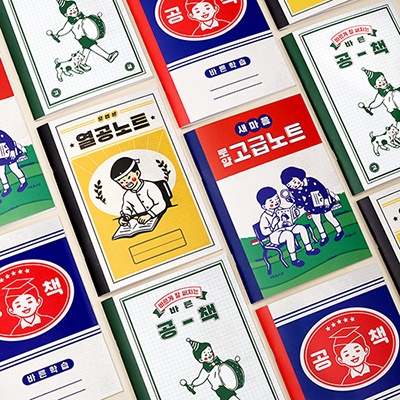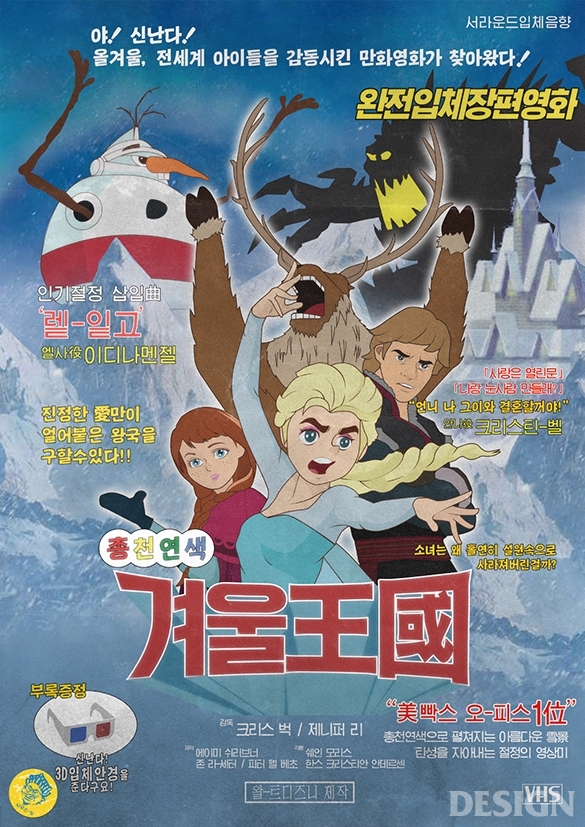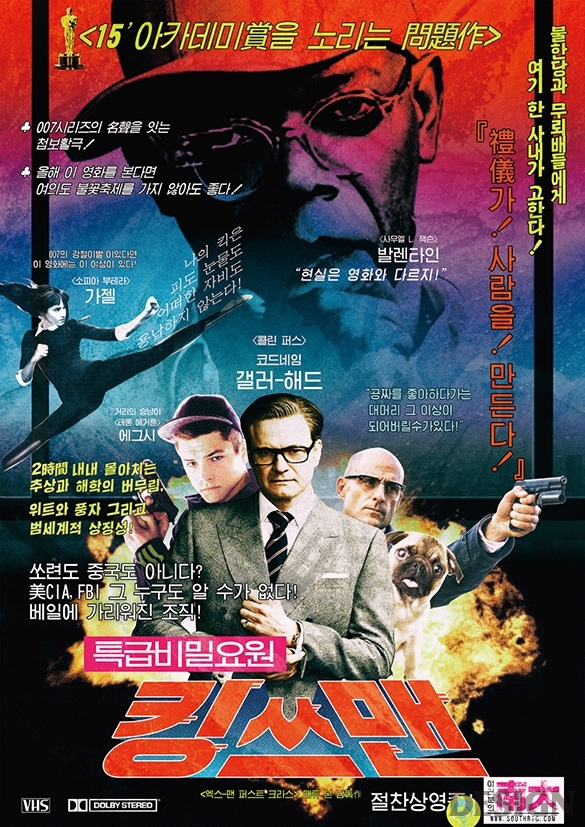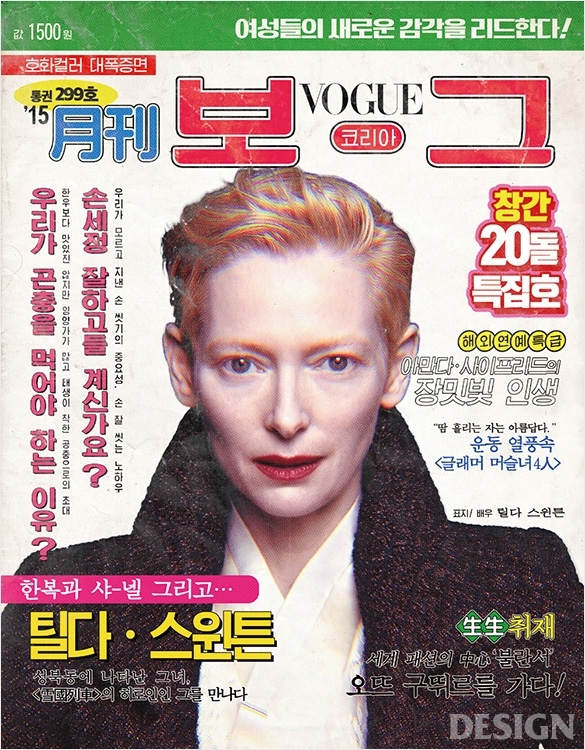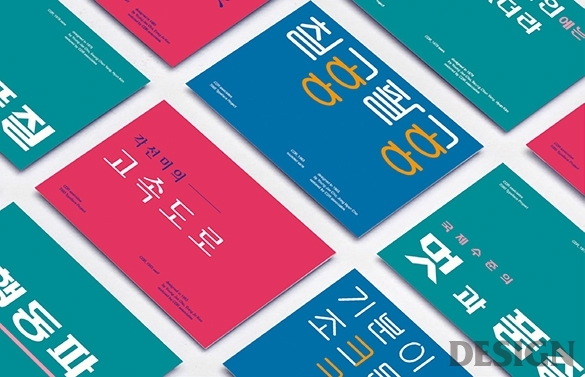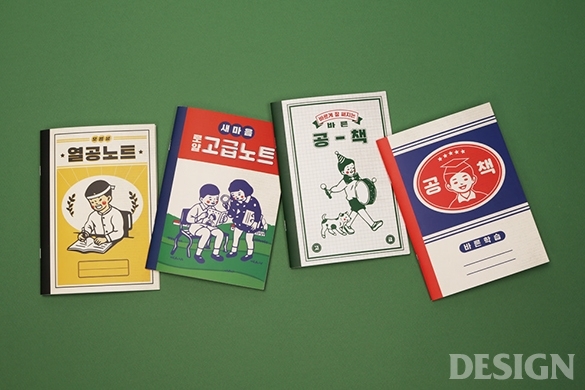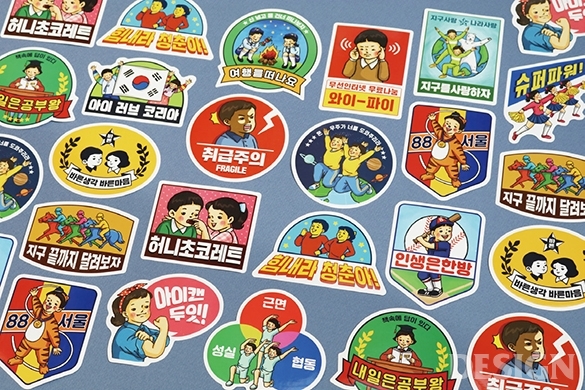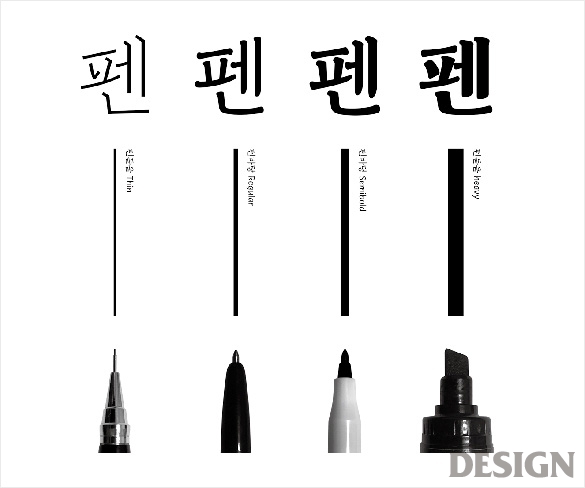
레트로 그래픽의 부상
2000년대 중반 들어 고개를 들기 시작한 레트로풍 타이포그래피와 그래픽 디자인은 이제 한국 디자인계에서 하나의 기조로 완전히 자리 잡은 모습이다. 이에 대한 심도 깊은 연구가 부족하다는 사실이 놀라울 정도다. 2000년대 말 붕가붕가레코드의 수석 디자이너 김기조가 선보인 레터링 작업(비록 이를 온전히 레트로로 보긴 어렵지만)은 당시 젊은 그래픽 디자이너들 사이에 적잖은 반향을 일으켰다. 수공업 소형 음반사를 지향하던 붕가붕가레코드는 크래프트지에 레터링을 입힌 라벨지를 부착하는 방식으로 비용을 절감했는데 그 모습이 영락없이 1970년대 말 폴라 셰어Paula Scher의 CBS 레코드의 아트 디렉터 시절을 연상시킨다. 제한된 예산에서 효과적인 결과물을 만들어야 했던 폴라 셰어의 상황이 2000년대 말 국내 인디 음반사의 그것과 일맥상통하는 것이다. 비슷한 시기에 젊은 타이포그래퍼들을 중심으로 그 옛날 도안사나 소위 간판장이의 글자를 모방한 것이 유행처럼 번져나가기도 했다.1) 이후 그래픽 디자인계에서 레트로 스타일은 여러 세대의 디자이너와 디자인 회사의 손길을 거치며 다양한 양상으로 표출됐다. 젊은 디자이너들은 레트로풍의 키치적 표현을 자신의 아이덴티티로 삼았고 기업들 역시 레트로를 앞세운 제품으로 시장을 공략했다. 디자인 저술가 전가경의 글은 그래픽 디자인, 특히 타이포그래피에서 다양하게 나타나는 레트로의 흐름을 짚어보는 데 도움이 될 것이다.
1) 혹은 북한 서체에서 영감을 받은 디자인이 나오기도 했다.
사우스빅의 <겨울왕국> 패러디 포스터는 2014년경 애니메이션의 성공과 더불어 큰 화제를 모았다. 이후로도 한동안 당대의 인기 영화를 1980~1990년대풍으로 재해석하는 작품을 연이어 선보였다.
시디알어소시에이츠의 7080폰트 복원 프로젝트. 시디알 창립자인 조영제 서울대학교 명예교수와 고 양승춘 교수, 김현, 조종현, 구동조 등 당시 왕성히 활동했던 디자이너들의 작업을 바탕으로 한 프로젝트로 텀블벅을 통해 공개했다.
역사 속 타이포그래피의 복고 현상
좁게는 타이포그래피, 넓게는 그래픽 디자인에서 ‘옛 제도나 모양, 정치, 사상, 풍습 따위로 다시 돌아감’을 뜻하는 ‘복고’는 낯선 게 아니다. 진부한 이야기이지만 현재는 언제나 참고된 과거의 일부이거나 변형이다. 18세기 서양에선 손글씨를 참고한 타이포그래피가 발전했다. 캐슬론, 바스커빌이 대표적이다. 이후 19세기의 보도니와 디도는 바스커빌을 기초로 획 대비가 강한 서체로 태어났다. 엘런 럽튼Ellen Lupton의 말대로 이 흐름은 ‘캘리그래피로부터 떨어져서 타이포그래피의 새로운 비전을 열어준’ 사건이었다. 윌리엄 모리스 또한 산업혁명에 반대하며 과거의 공예 정신을 상기시키는 복고를 감행했고 에드워드 존스턴Edward Johnston이 다시 이 정신을 이어받아 더 오래된 과거인 중세 시대를 글자로 소환했다. 물론 전통에 대한 참고가 항상 지배적이었던 것은 아니다. 파울 레너, 헤르베르트 바이어, 얀 치홀트 등 20세기 초반의 타이포그래피 개혁자들은 반역사주의적 태도를 취했다. 전통주의와 개혁주의의 노선이 공존했고 타이포그래피에서 전통으로의 회귀나 복고주의적 태도는 어제오늘의 일이 아니다.
15세기 훈민정음 창제 이후 전개된 한국의 타이포그래피도 예외일 순 없다. 탈네모꼴이 전위적 한글을 대표한다면, 본문용 서체로 군림하고 있는 명조체는 붓글씨를 기반으로 한다. 과거는 더 앞으로 나아가기 위한 인용 혹은 반동의 대상이자, 근미래의 방향 전환을 위한 판단 기준이다. 몇 가지 역사적 사실에도 불구하고 우리는 지난 몇 년간의 타이포그래피 혹은 그래픽 디자인의 특정 흐름을 ‘복고’ 혹은 ‘레트로’라고 뭉뚱그린다. 개화기나 일제강점기 혹은 1970~1980년대를 상기시키는 굵은 획의 정방형 글자, 그리고 이와 결탁한 ‘00상점’, ‘00여관’, ‘00당’ 등의 네이밍은 특정 시대를 적극 소환한다는 측면에서 복고이다. 몇 년째 디자인·미술 분야 베스트셀러 상위권을 독차지하고 있는 손글씨 및 캘리그래피 교본들 또한 이러한 복고 열기와 무관하지 않다. 최소한 지금 이 시점에서의 복고는 디지털 시대 이전의 아날로그 감성을 함축하기 때문이다. 그런데 이 현상을 바라보는 우리의 시선이 과연 섬세한지 물어본다면 대답은 부정에 가깝다.
일단 ‘복고’라는 항목에 넣을 수 있는 타이포그래피 아이템을 열거해보자. 크게는 레터링과 폰트로 구분할 수 있다. 한글 레터링의 전성기는 1980년대였다. 급변하는 사회상을 글자로 담아내기에 당시 사용했던 납활자와 사진식자는 한정적이었다. 당시 잡지사나 신문사 일을 하던 수많은 익명의 디자이너들은 좀 더 풍부한 표정의 글자를 표현하고자 직접 글자를 도안했다. 1950~1960년대 한글 레터링의 특징이 정제되지 않은 날카로움이라면, 1970년대 후반부터 전개된 글자 도안은 ‘작도’에 힘입어 보다 현대적 풍채를 지니게 된다. 당시 레터링은 일종의 반동이었다. 글자라는 자원의 한계를 극복하기 위해 김진평, 이상철, 서시철 등의 디자이너는 레터링으로 글자를 제작했다. 한글 레터링의 전성기는 글자 자원의 고갈 앞에서 디자이너들이 개척해나가야 했던 새로운 타이포그래피의 지평이었다. 물론 독재 정권이라는 정치적 배경만큼이나 당대 레터링이 담아낸 메시지 또한 상하 위계질서의 조형적
상징이긴 했다.
21세기형 레트로
레터링의 새로운 부활은 2008년 김기조가 진행한 인디 밴드 ‘장기하와 얼굴들’의 앨범 레터링 작업과 결부된다. 복고적 성향이 강한 ‘장기하와 얼굴들’에 어울리는 글자로 김기조는 1970~1980년대를 연상시키는 레터링을 디자인했다. 이후 그는 자기 주도적 차원의 문장형 레터링을 선보이며 한글 레터링 작업을 전개했다. 많은 이들은 그의 타이포그래피를 ‘복고’ 혹은 ‘레트로’와 연결시켰고 유사한 작업이 성행했다. 그러나 이는 ‘장기하와 얼굴들’이라는 음악 밴드와의 협업으로 인한 일종의 착시 현상이었다. 당시는 전 세계적으로 음악 신이 레트로 열풍을 앓고 있을 때였다. 김기조는 복고적 음악에 어울리는 타이포그래피로 화답했다.
막상 그가 선보인 자기 주도적 레터링은 반복고적이었다. 김기조 타이포그래피의 묘미는 조형적 복고성 이면에 담아낸 메시지의 반전 효과에 있다. 조형적으로는 복고적 형식을 차용했으나, 88만 원 세대의 시니시즘(냉소주의)이 유쾌하게 반영된 새로운 레터링이었다. 거기에 과거에 대한 노스탤지어는 없었다. 문제는 이에 대한 수용과 분석이 부재했다는 것이다. 그런 의미에서 공식 출시 전부터 큰 관심을 받았던 양장점의 펜바탕체에 대해서도 섬세한 접근이 필요하다. 펜바탕체를 복고의 범주에 넣기엔 무리가 따르는데, 기존 붓글씨 기반의 본문용 서체 환경을 넘어 펜 기반의 본문용 서체를 개발했다는 배경 때문이다. 펜바탕체는 분명 손글씨 및 캘리그래피 교본 그리고 컬러링북의 요란스러운 인기를 연상시키는 아날로그의 기운이 물씬 풍기지만, 필기구의 다양성 측면에서 본문용 폰트를 평가할 때 ‘복고’라는 이름으로 일반화하기엔 무리가 있다.
반면 표면적으로는 과거의 레터링 조형을 취하고 있지만 특정 시대를 노골적으로 소환하는 폰트 회사들의 다양한 복고 폰트가 있다. 산돌은 2014년 격동고딕체, 단팥빵체, 광야체를 시작으로 2015년 개화체, 별표고무체, 격동굴림체, 국대떡볶이체, 2016년 격동명조체, 크림빵체, 시네마극장체, 그리고 2017년에는 로타리체, 프레스체, 청류체 등 다양한 복고 폰트를 야심 차게 내놓았다. 각 서체는 특정 시대를 명료하게 소환한다. 배달의민족에서 무료 배포하는 한나체와 도현체도 이 흐름에 가세한다. 네이밍도 특정 시대를 연상케 하는 데 한몫한다. 미쓰리체, 장미다방체, 옛날목욕탕체 등으로 목록이 이어진다. 이는 전형적 복고이다.
다프트펑크가 2015년경 선보인 레트로 포스터. 공식 웹사이트에서 판매하던 제품을 1980년대풍으로 표현했다.
산돌티움의 바른생활 시리즈. 빈티지 콘셉트에 맞춰 대부분 산돌격동고딕체를 사용했다.
양장점의 펜바탕체.
김기조의 레터링.
섬세한 집도가 필요한 복고 현상
‘복고’라는 용어로 눈에 드러나는 현상을 기술하기 이전에 과거를 인용, 차용, 소환하는 방식의 다양성에 대해 재고해볼 필요가 있다. 이 현상에서 가장 아이러니한 점은 한글 서예의 전통을 이어온 손멋글씨 혹은 캘리그래피가 복고로 지칭될 수 있는 문화 현상에서 누락되어 있다는 점이다. 이는 결국 복고라는 이름하에 호출되는 특정 과거와 조형이 있음을 반증한다. 해외에서 ‘레트로 타이포그래피’가 보다 광범위한 시대에 걸쳐 논의된다는 사실도 이를 입증한다. 전 세계적 레트로 현상을 팝 음악 신에 한정 지어 논한 사이먼 레이놀즈의 표현을 곱씹어볼 필요가 있다. 복고는 ‘보존주의 운동’ 혹은 ‘고풍 조작 운동’인가? 이에 열광하는 자는 ‘과거주의자’인가? 이에 열광하지 않는 자는 그럼 ‘미래주의자’로 분류할 수 있는가? 복고의 윤곽을 성급하게 그리기 이전에 현상을 기술할 수 있는 섬세한 용어들이 나와줘야 할 것이다.